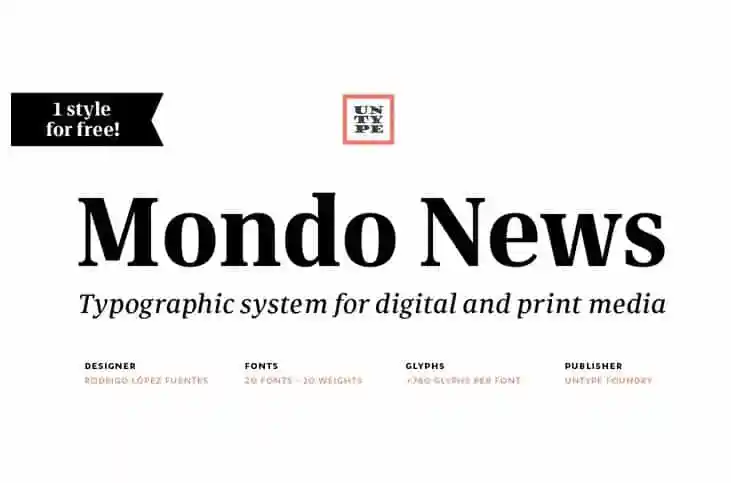
Mondo News Serif Font – Download Grátis
A Mondo News Serif Font é uma tipografia serifada contemporânea inspirada nas dinâmicas vividas atualmente, especialmente no contexto das quarentenas e pandemias. Cercada por momentos de isolamento social e incerteza, a Mondo News foi projetada pelo designer Untype para atender às necessidades editoriais tanto do digital quanto do papel. Este tipo de fonte oferece um equilíbrio cuidadosamente elaborado entre proporções levemente estreitas e uma altura significativamente grande da letra “x”, permitindo a máxima performance sem comprometer a legibilidade. Com sua rica história tipográfica e arquitetura elegante, ela é perfeita para publicações editoriais modernas que buscam um estilo profissional e vibrante, capaz de transmitir confiança e autoridade. Engane-se se pensasse que as fontes serifadas tradicionais são apenas sombrias: a Mondo News Serifa apresenta uma frescura e um vigor que certamente enriquecerá suas páginas digitais ou impressas.